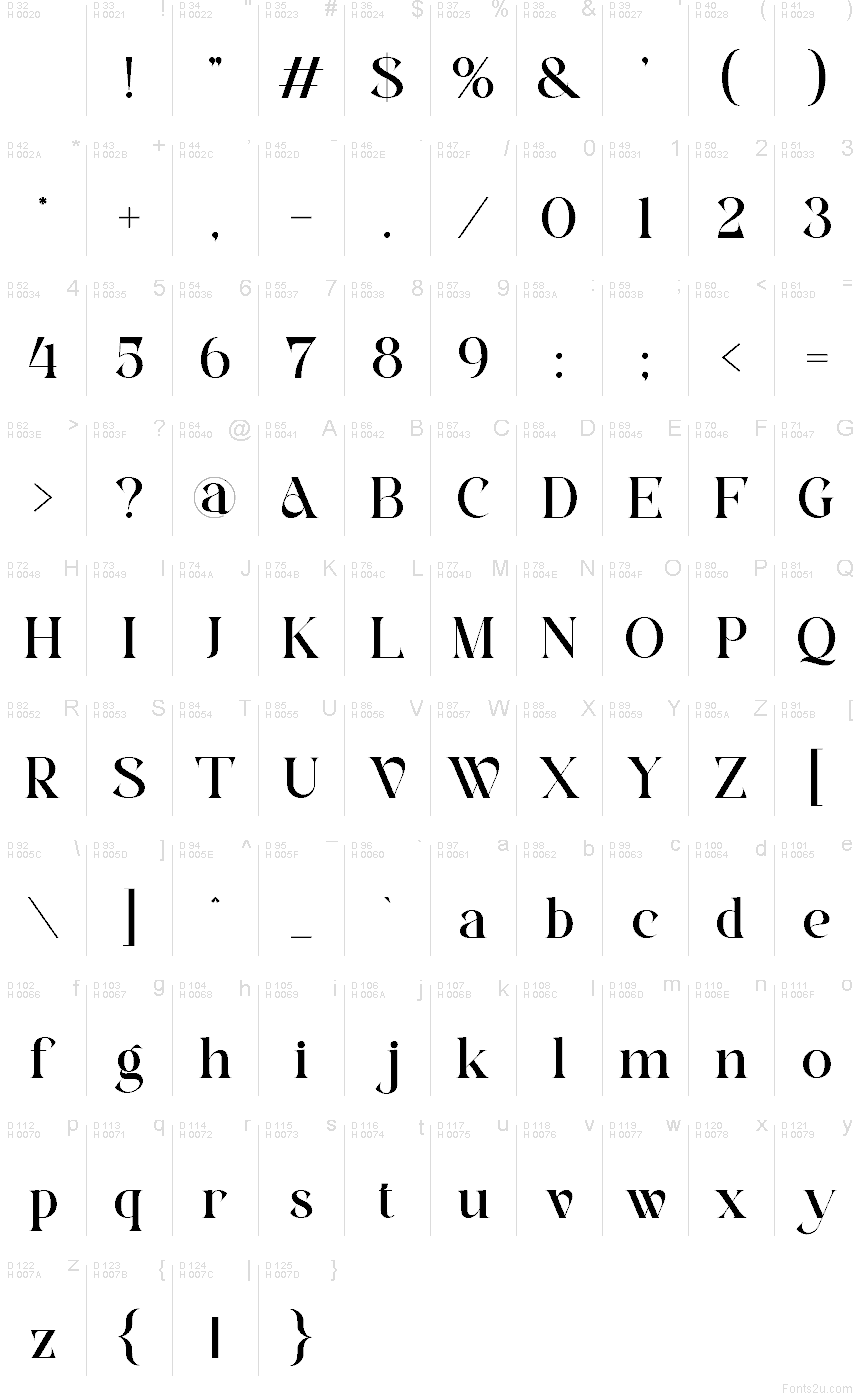
Desenvolvida pela Ermedia Studio, Ectros é uma fonte serifada gratuita e de alto contraste, criada para trabalhos refinados de exibição contemporânea com uma marcante veia editorial e teatral. Letras alongadas e de espaçamento reduzido reúnem curvas arredondadas amplas, traços de união ultrafinos e hastes verticais imponentes, enquanto as formas mais largas utilizam barras horizontais estendidas e junções estreitas para compor uma silhueta nobre, elegante e impecavelmente desenhada.
O branding de moda é o seu campo de atuação mais natural, em especial em embalagens de perfumes de luxo e capas de revistas sofisticadas, nas quais o contraste marcante entre traços grossos e finos dialoga com fotografias com brilho, frascos esculturais e as linhas precisas da alta-costura. O modelo também confere elegância teatral a cartazes de galerias e eventos artísticos de destaque.